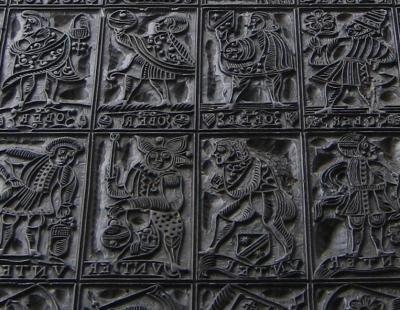
Suche nach Schrift auf Altenburger Skat-Karten (Frz. Bild)
ich versuche herauszufinden, mit welcher Schriftart die Skat-Karten der Fa. Altenburger gekennzeichnet sind.
Ich halte es für gar nicht unwahrscheinlich, dass es sich dabei um handgezeichnete Buchstaben handelt, will aber trotzdem mal die Frage ins Experten Forum stellen. (Ich habe die einschlägigen Font-Finder ergebnislos durchsucht)
Gelöst von catfonts
Ich halte es für gar nicht unwahrscheinlich, dass es sich dabei um handgezeichnete Buchstaben handelt
Genau das wird es sein, denn die Druckstöcke für das original Altenburger Französische Blatt sind uralt.
So sehen solche Druckstöcke aus:
Da Bleibuchstaben reinzufummeln, macht wenig Sinn. Sagt sogar die gerade verlinkte Seite auch:
Der klassische Buchdruck mit beweglichen Lettern ist für Spielkarten weniger geeignet, da für Karten viel Bild und wenig Text zu drucken ist.
Ich verfüge über eine ganze Reihe digitaler (lizensierter) Versionen von Altenburger Spielkarten – Auf diesen Karten ist die Positionierung der Kartenwerte/Kennzeichnung keineswegs ausgerichtet, sondern die Buchstaben und Zahlen springen fröhlich in der Ecke herum. Zudem scheint es keine vektorisierten Versionen dieser Kartenbilder zu geben (auch nicht von moderneren Versionen wie z.B. einem Pokerblatt).
All das bestärkt mich in der Annahme, dass die ganzen Karten, Bilder und Buchstaben/Werte, auf handgezeichneten Vorlagen beruhen. (Die recht unterschiedliche Ausführung der Zahlen gegenüber den Buchstaben spricht ebenfalls dafür)...